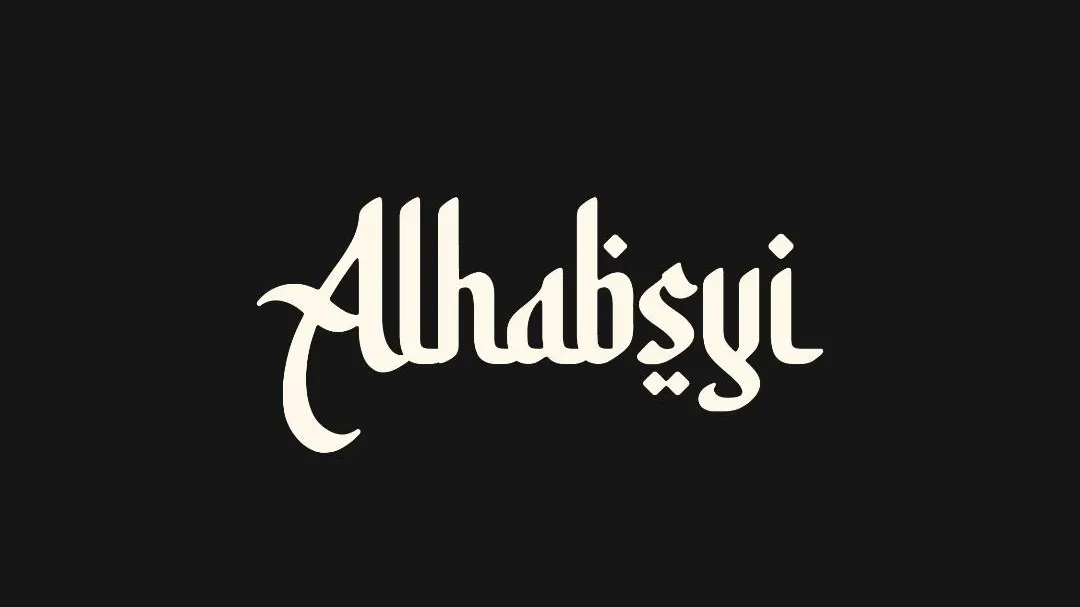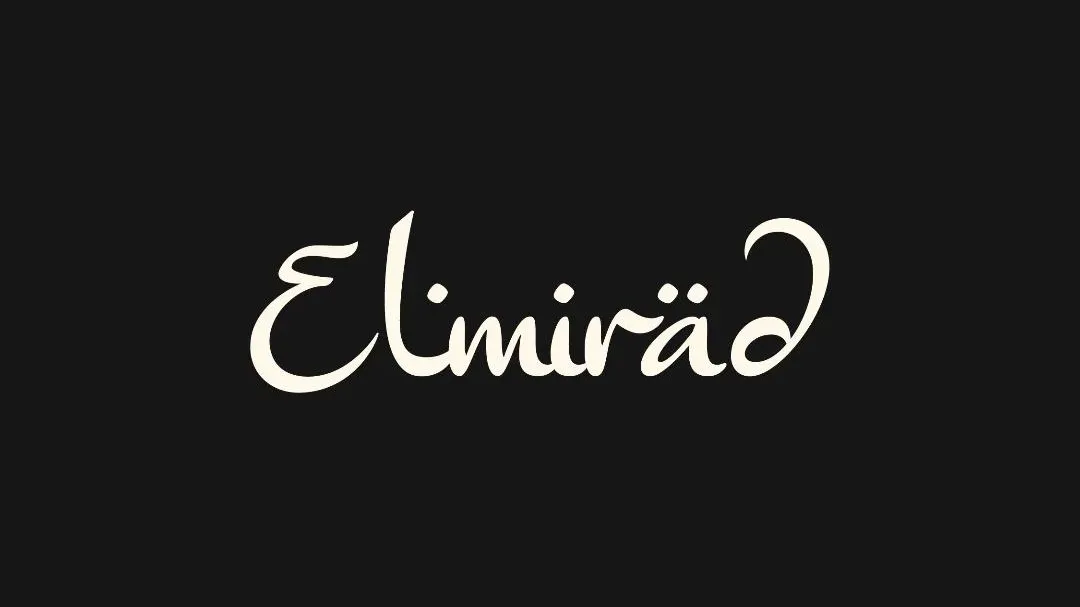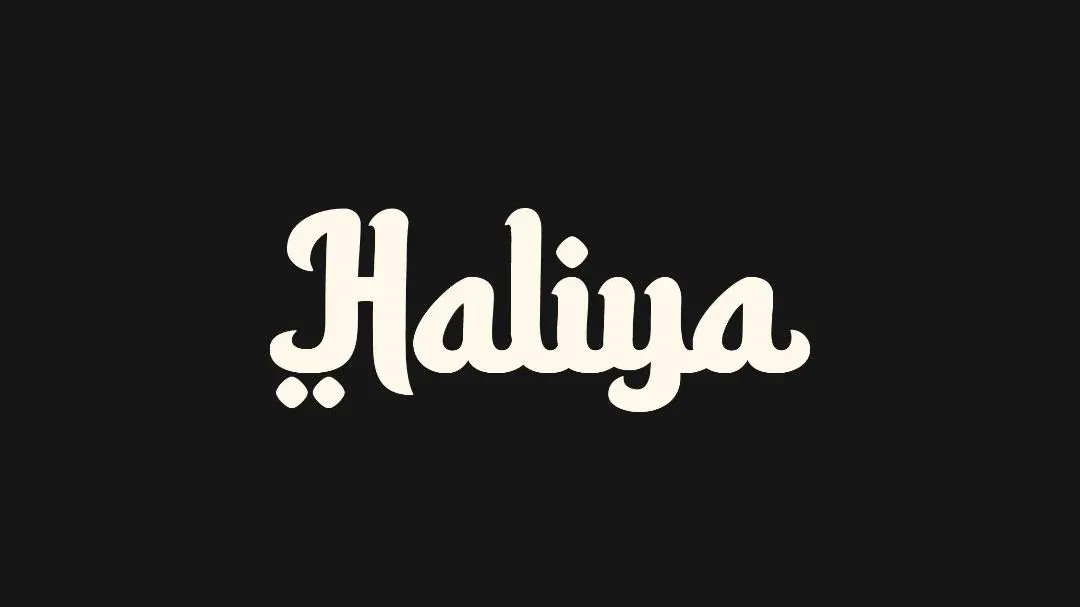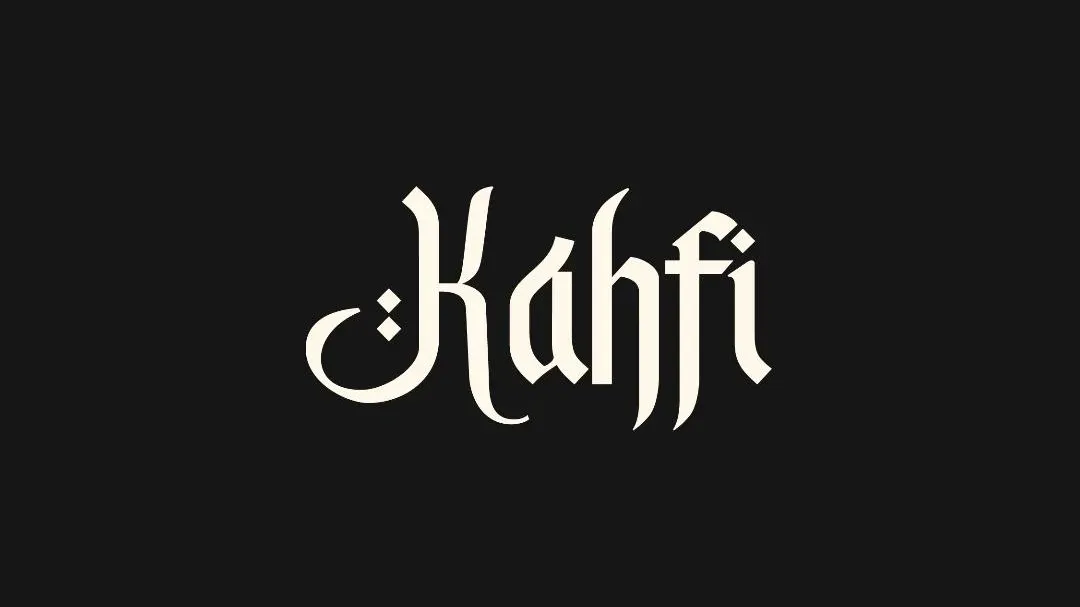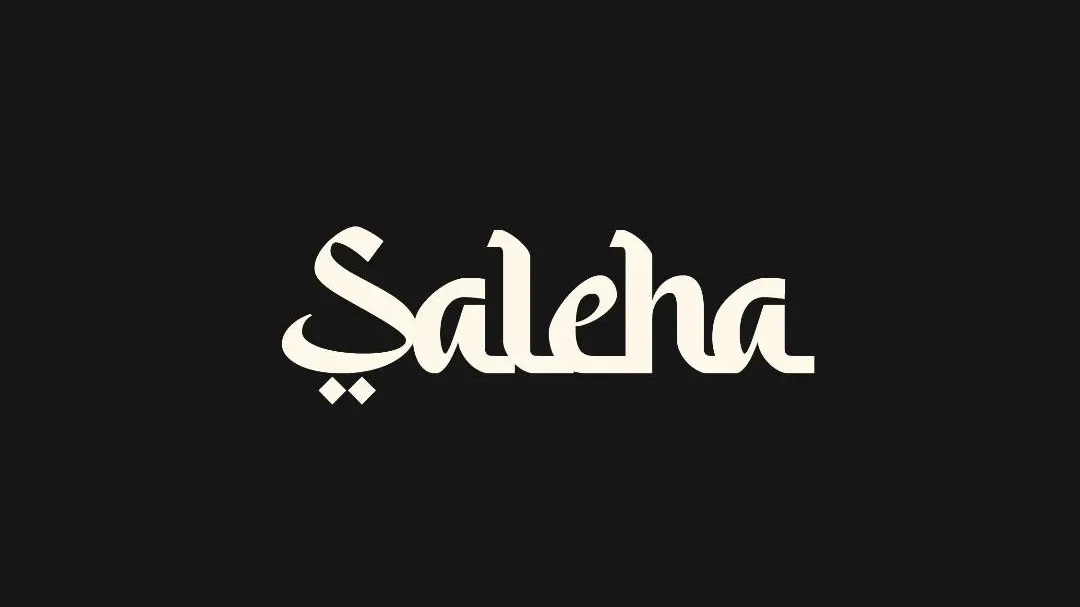
Memilih Font Arabic Style: Kapan, Dimana dan Bagaimana Menentukan Pakai yang Mana
Memilih 5 Font Bernuansa Arab: Karakteristik, Feel, dan Rekomendasi Penggunaannya. Pilih font yang mana, kapan, dimana dan bagaimana menentukan untuk memakainya.
Memilih Font Arabic Style: Kapan, Dimana dan Bagaimana Menentukan Pakai yang Mana
Memilih font yang tepat adalah seni menyampaikan pesan tanpa kata. Khususnya untuk font bernuansa Arab/kaligrafi Islami, pemahaman karakteristik dan feel-nya menentukan kesuksesan desain.
Mengapa Font Bernuansa Arab Istimewa?
Font kaligrafi Arab bukan sekadar tipografi, ia membawa identitas budaya:
• Simbol Spiritualitas: Mengomunikasikan nilai religius dan tradisi
• Estetika Organik: Lekukan dinamis mencerminkan seni Islam yang cair
• Identitas Kultural: Penguatan merek berbasis budaya Timur Tengah/Asia Selatan
Penjelasan Feel, Karakteristik 5 Font Arabic Style Font (Nuansa Islami) & Rekomendasi Pemakaian
Font kaligrafi Arab adalah jiwa visual yang menyampaikan cerita budaya. Setelah verifikasi mendetail terhadap sampel aktual, berikut panduan untuk 5 font unggulan bernuansa Arab atau Islami:
1. Alhabsyi Font
Alhabsyi
• Karakteristik Visual:
• Stroke sedang dengan keseimbangan sempurna antara tebal dan tipis
• Lengkungan oval konsisten dan ruang negatif harmonis
• Garis vertikal ramping memberikan kesan elegan namun stabil
• Nuansa Emosional:
• Sopan
• Terpelajar
• Kontemporer
• Rekomendasi Penggunaan:
• Sistem identitas sekolah Islam/prestigious madrasah
• Kartu nama profesional (ulama, dosen studi Islam)
• Desain aplikasi edukasi Al-Qur’an digital
Tip Teknis: Ukuran minimal 18pt, Tracking -5%, Kombinasi Navy + Emas
2. Elmirad Font
Elmirad
• Karakteristik Visual:
• Geometri modular dengan potongan diagonal tak terduga
• Dekonstruksi bentuk dasar (kotak+lingkaran) yang terencana
• Kesatuan visual melalui ritme sudut tajam
• Nuansa Emosional:
• Avant-garde
• Dinamis
• Visioner
• Rekomendasi Penggunaan:
• Branding festival seni Islam kontemporer
• Desain cover album musik fusion Timur-Barat
• Visual konferensi teknologi syariah
Tip Teknis:
Ukuran minimal 24pt, Tracking +10%, Kombinasi Hitam + Neon Cyan
3. Haliya Regular
Haliya
• Karakteristik Visual:
• Geometri modular dengan potongan diagonal tak terduga
• Dekonstruksi bentuk dasar (kotak+lingkaran) yang terencana
• Kesatuan visual melalui ritme sudut tajam
• Nuansa Emosional:
• Avant-garde
• Dinamis
• Visioner
• Rekomendasi Penggunaan:
• Branding festival seni Islam kontemporer
• Desain cover album musik fusion Timur-Barat
• Visual konferensi teknologi syariah
Tip Teknis: _Ukuran minimal 24pt, Tracking +10%, Kombinasi Hitam + Neon Cyan.
4. Kahfi Font
Kahfi
• Karakteristik Visual:
• Tekstur kuas ekspresif dengan tekanan variatif
• Garis fraktal dan tinta tak sempurna yang artistik
• Karakter unik (misal: bentuk “f” ganda) penuh persona
• Nuansa Emosional:
• Ekspresionis
• Urban
• Bebas
• Rekomendasi Penggunaan:
• Branding streetwear komunitas muslim muda
• Poster event seni independen bernuansa Islami
• Kemasan produk kreatif UMKM lokal
Tip Teknis: Ukuran minimal 30pt, Tracking -3%, Kombinasi Earth tone + Oranye
5. Saleha Font
Saleha
• Karakteristik Visual:
• Kaligrafi Naskh modern dengan ligatur rumit.
• Ornamen floral tersembunyi dalam struktur huruf.
• Kontras tebal-tipis dramatis seperti pen-dance.
• Nuansa Emosional:
• Ornamental
• Festif*
• Naratif
• Rekomendasi Penggunaan:
• Stage design pernikahan mewah bergaya Ottoman
• Kemasan produk koleksi edisi spesial mewah
• Ilustrasi cerita rakyat Seribu Satu Malam
Tip Teknis: Ukuran minimal 36pt, Tracking +5%, Kombinasi Deep Green + Perak
Contoh Pemilihan Berdasarkan Kebutuhan
Kebutuhan DesainSolusi FontContoh Implementasi
Pendidikan IslamAlhabsjiBuku teks, Sistem LMS madrasah
Seni KontemporerElimiracKatalog pameran, Merchandise seni
Elegan MinimalisHaliyaKartu ucapan premium, Desain logo
Ekspresif/YouthKahfiKaos komunitas, Poster musik
Kemasan MewahSalahaKotak parfum, Sertifikat emas
Aturan Penggunaan Font Kaligrafi
Setidaknya 4 hal yang harus diperhatikan saat ingin memakai font arabic style atau font nuansa islam:
1. Prinsip Hierarki
• Gunakan font kaligrafi hanya sebagai display (judul/logo).
• Pairing dengan font sans-serif minimalis (e.g., Poppins, Inter) untuk teks deskripsi.
2. Keterbacaan adalah Raja
• Uji keterbacaan di berbagai ukuran dan latar belakang.
• Hindari kaligrafi kompleks di media kecil (e.g., kartu nama).
3. Respek Budaya & Lisensi
• Pastikan penggunaan sesuai konteks budaya (e.g., hindari font sakral untuk desain trivial).
Kelima font ini menawarkan kisah berbeda: dari kemewahan Saleha hingga kehangatan Kahfi. Kunci suksesnya? Konteks. Pilih font yang tidak hanya indah, tapi juga menyampaikan jiwa proyek Anda.